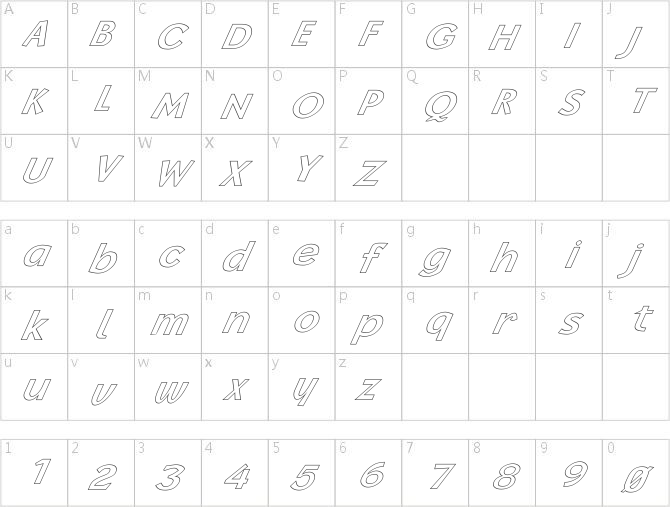
FZ BASIC 14 HOLLOW ITALIC 詳情頁
FZ BASIC 14 HOLLOW ITALIC字體字庫是一款讓人賞心悅目、百看不厭的英文字體,適合各類廣告和產(chǎn)品包裝設(shè)計(jì)應(yīng)用,字體大小0.04MB,格式為ttf字體,上傳用戶是東方時(shí)尚,作者/版權(quán)方為未知